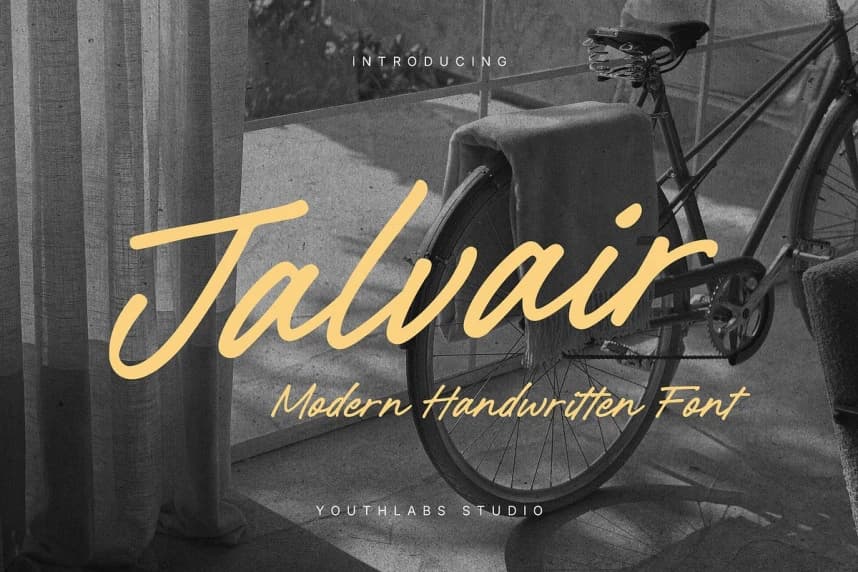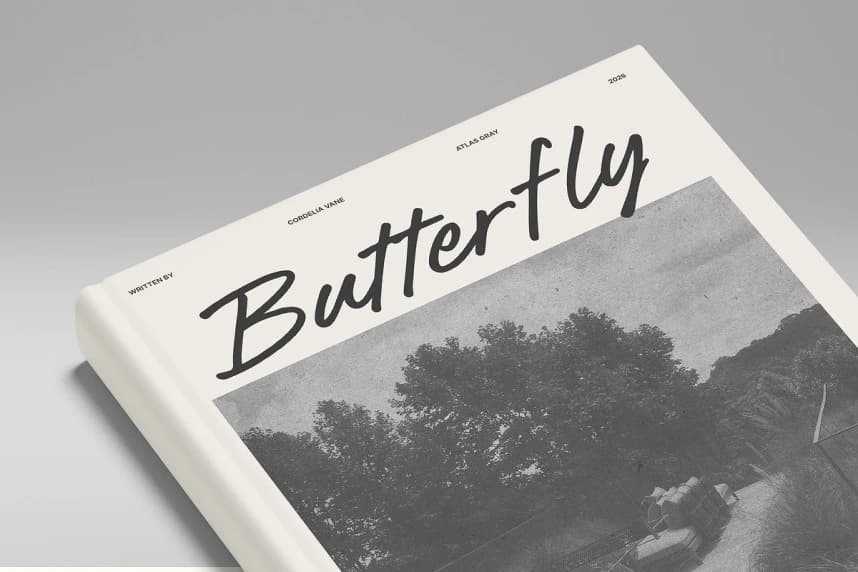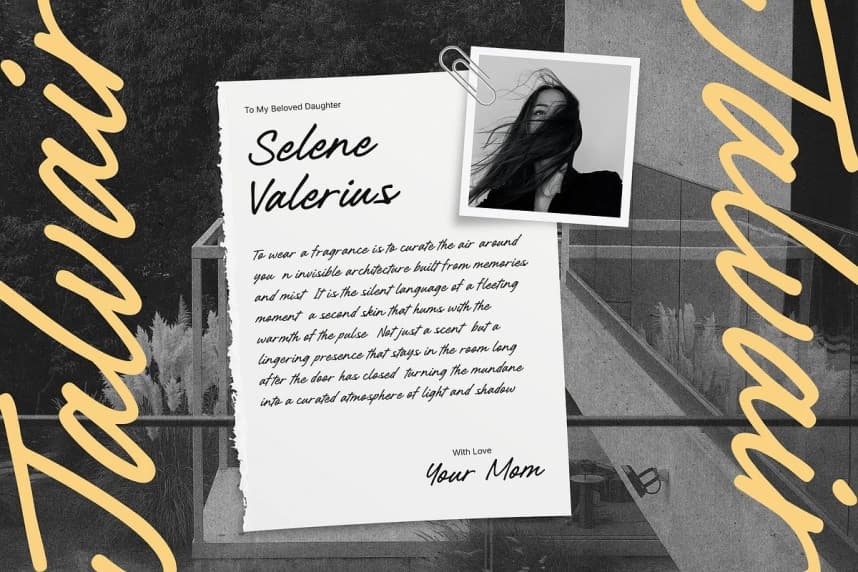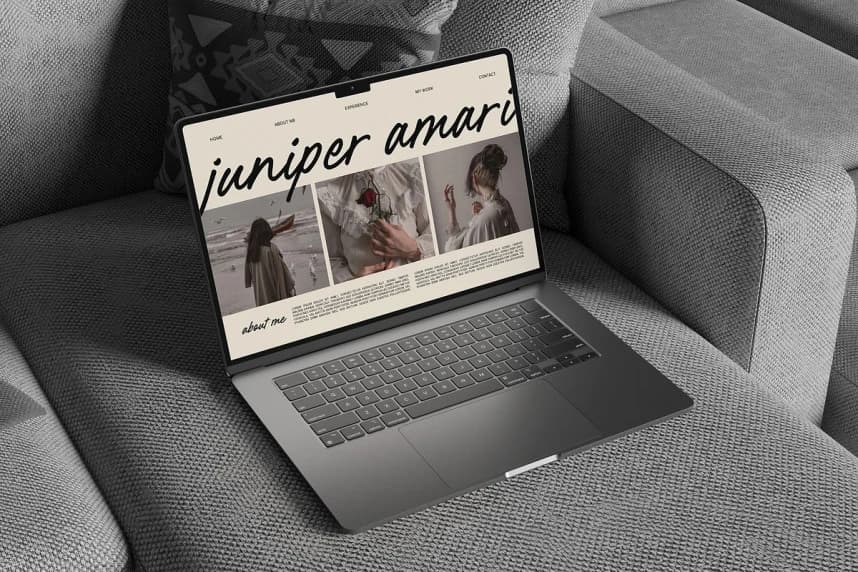
Jalvair – Modern Handwritten Font
Jalvair - Modern Handwritten Font, gündelik kalem tutuşunun zahmetsiz cazibesini yakalayan modern bir el yazısı fontudur. Bu yazı tipi, kalın ve gündelik çizgileriyle ritmik, organik bir akış sağlar ve bu akış anında tanıdık ve sıcak bir his verir.
Jalvair - Modern Handwritten Font, günlük kalem yazımının zahmetsiz cazibesini yakalayan modern bir el yazısı fontudur. Bu yazı tipi, kalın ve sade çizgileriyle ritmik, organik bir akış sağlar ve anında tanıdık, sıcak bir his verir.
Jalvair – Modern Handwritten